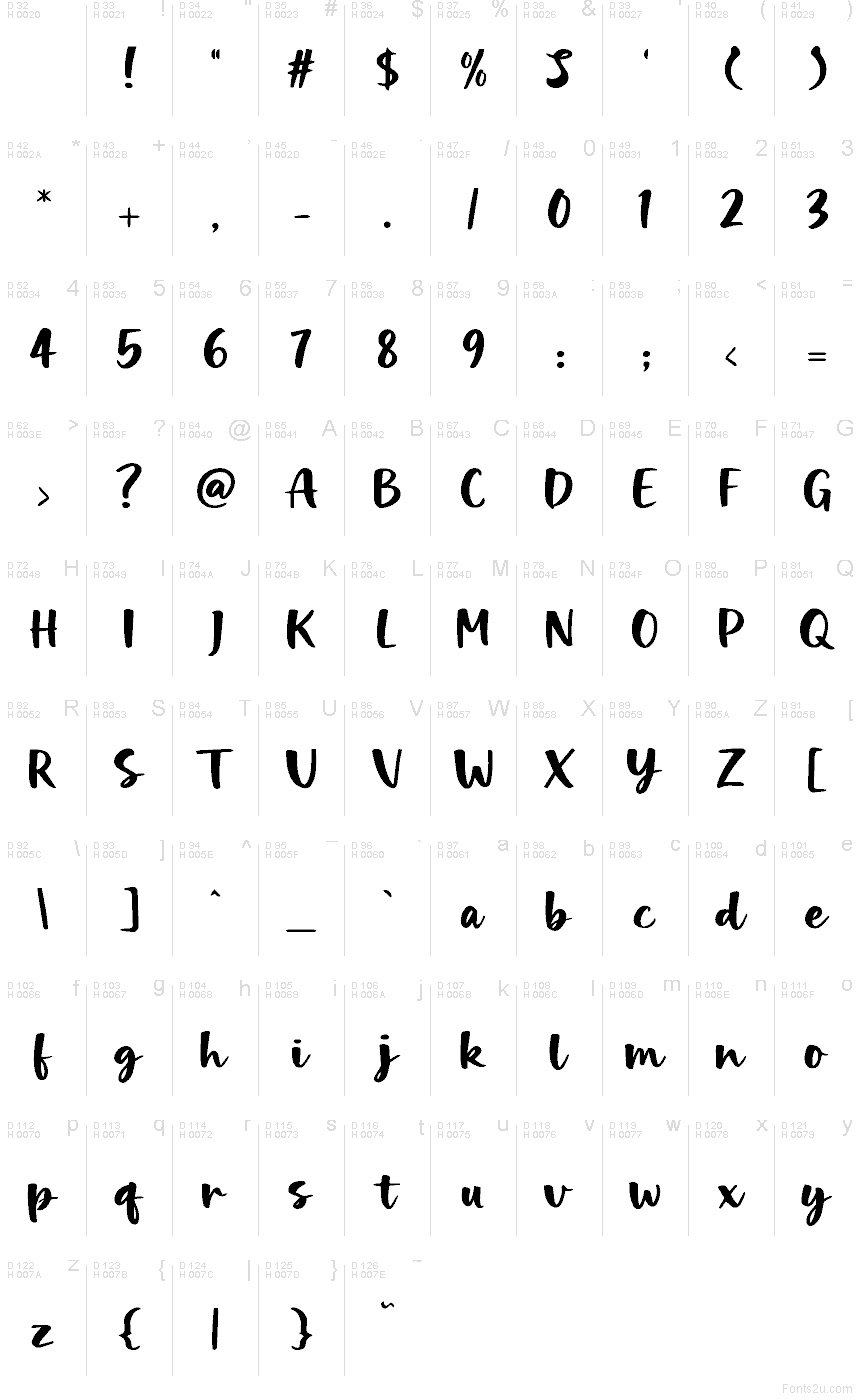
Abricot Sensuel
Abricot Sensuel от BlackFridayFont — это бесплатный шрифт в стиле brush script с мягким, непринужденным ритмом и округлыми штрихами, которые выглядят так, будто их нарисовали кистью, а не вычертили. Буквы следуют современной рукописной эстетике: сочетание плотной вертикали с быстрыми изгибами и мелкими акцентами делает линию живой, но не перегруженной.
Шрифт отлично подойдет для косметических брендов, упаковки кофеен, цитат в соцсетях, заголовков приглашений и журнальных обложек — везде, где требуется бесплатный шрифт, добавляющий теплоты и кокетства. Используйте его в коротких фразах, логотипах или заголовках: энергичный поток и характерный контраст мазков лучше всего смотрятся в лаконичных надписях.